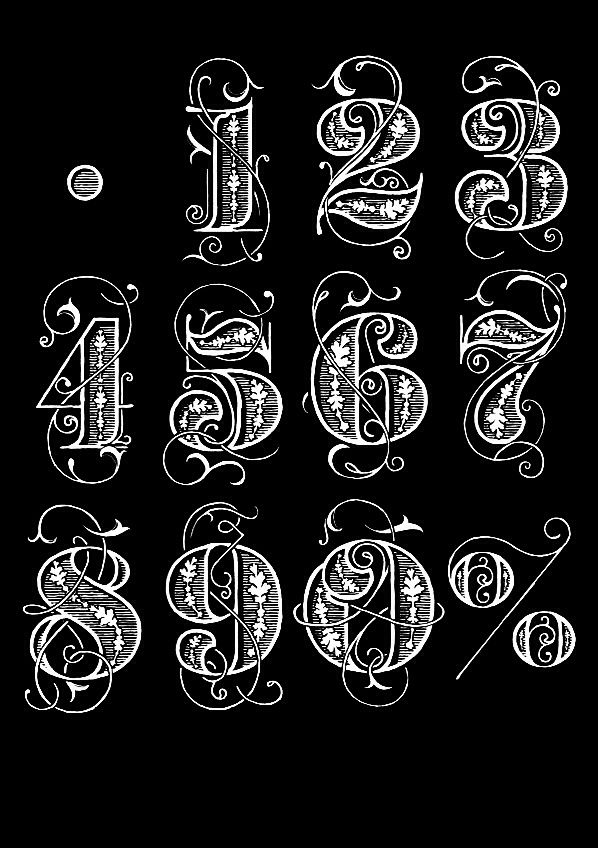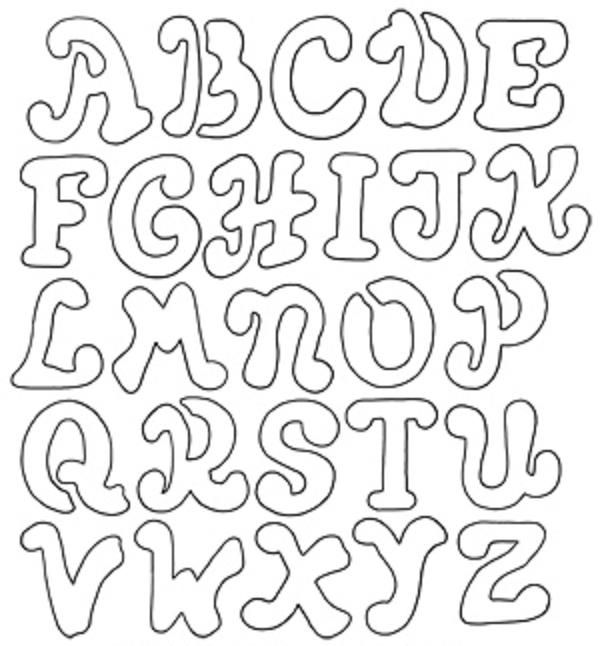
Шрифт для букв красивый шрифт для вырезания: Трафареты и шаблоны букв для вырезания из бумаги
Как красиво написать буквы для оформления плаката, стенда.
Из этой статьи вы узнаете, как сделать красивую надпись для оформления плаката, стенда, Дня рождения или любого другого праздника.
Красивые русские буквы печатные красивым шрифтом для оформления: шаблоны букв, распечатать и вырезать
Организовать праздник можно и без тематических надписей, но если вы готовите стенд, плакат, то одних фотографий или картинок будет недостаточно: ведь нужно, как минимум, написать поздравление. Без текста не обойтись при оформлении праздника. Необычные и оригинальные шаблоны букв пригодятся и в рекламной индустрии, в качестве декораций, дополняющих тематику мероприятия.
Без текста не обойтись при оформлении праздника
- Чтобы не искать шаблоны каждый раз перед очередным мероприятием или событием, можно найти подходящие трафареты и вырезать их на плотном картоне. Такие заготовки подойдут для многократного использования.
- Нужно будет только приложить трафарет к выделенному под надпись месту на плакате или стене и аккуратно нанести тонкий слой краски. Заполнять буквы нужно так, чтобы краска не подтекала под трафарет.
- Вы сможете прекрасно провести время с ребенком при подготовке к празднику. Сам процесс написания текста заинтересует малыша, совместное занятие будет способствовать развитию памяти, пробуждать творческую деятельность. Также благодаря вырезанию букв у ребенка будут формироваться первоначальные знания азбуки.
Как написать красивую надпись
- Вырезать буквы по контуру можно ножницами. Но удобнее делать это канцелярским ножом.
Красивые буквы наносятся краской прямо на бетонную поверхность или покрытую асфальтом. - На деревянную поверхность, металлическую, на кирпичи также можно наносить графические элементы.
Зная технологию нанесения букв на поверхность, вы сможете самостоятельно сделать надпись для любого объекта производства, прорекламируете сферу услуг.
- Буквы, написанные по заранее подготовленному шаблону, выглядят аккуратно и четко, а фантазировать и подбирать различные варианты для написания текста можно бесконечно.
Зная технологию нанесения букв на поверхность, вы сможете самостоятельно сделать любую надпись
Варианты красивых печатных букв:
Вариант красивого печатного шрифта №1
Вариант красивых печатных букв №3
Вариант красивых печатных букв № 4
Красивые русские буквы прописные для оформления: шаблоны букв, распечатать и вырезать
Если вам нужно сделать надпись прописными буквами, то поищите подходящий вариант в этом разделе.
Красивые русские буквы прописные для оформления: вариант № 2
: шаблоны букв, распечатать и вырезать
В этом разделе вы найдете подборку красивых русских букв для оформления новогоднего мероприятия.
Красивые русские буквы новогодние для оформления
Красивая новогодняя надпись для оформления
Красивые русские буквы новогодние для оформления
Чтобы сама надпись на поминала о зимних морозных ясных деньках, стоит поискать для оформления праздника и соответствующие шаблоны букв. Чтобы облегчить вам поиски, мы собрали их в этом разделе.
Красивые русские буквы заглавные для оформления: шаблоны букв, распечатать и вырезать
- В художественных школах и других профильных учебных заведениях годами учат создавать надписи, правильно располагать тексты на плакате. Потому всех нюансов написания букв не раскрыть в рамках одной статьи. Да мы и не будем пытаться. Ведь сейчас есть масса способов обойти процесс написания текста: буквы и целые надписи можно распечатать на принтере, перерисовать с готовой афиши, обложки на кальку, а потом перевести на плакат или другую поверхность.
- При необходимости можно просто приклеить распечатанный на черно-белом или цветном принтере текст. Но если есть время, то можно и поэкспериментировать с цветами, фактурой и нанести краску каким-то необычным способом.
Какие инструменты понадобятся для написания красивого текста
Красивые русские буквы заглавные для оформления
Красивые русские буквы с вензелями для оформления: шаблоны букв, распечатать и вырезать
- Начинайте работу с создания эскиза. Вы сократите себе время, потраченное на создание плаката или надписи для мероприятия, если напишете текст в маленьком формате, отобразив максимальное количество деталей.
- Во время подготовки эскиза у вас должно сложиться четкое представление о том, какой должна получиться в итоге ваша надпись. К чистовому исполнению можно будет приступить только после предварительных зарисовок.
Решение о расположении текста также нужно принять на этапе создания эскиза. - Приступая к написанию текста, стоит придерживаться простого и нехитрого правила: все знаки должны иметь одинаковую ширину. Также надпись должна состоять из одинакового сочетания тонких и широких линий. Не допускайте написания графических элементов внахлест, знаков разной высоты, разной длины или ширины. Между буквами, в каком бы формате вы их не создавали, должно сохраняться одинаковое расстояние.
Конечно такой хаос не подходил римлянам, когда с расцветом своей империи они позаимствовали греческую письменность и алфавит. И вот тогда для уравновешивания формы букв и придания им законченной формы, они придумывают первые засечки:
Переходная ранняя форма римского капитального шрифта.